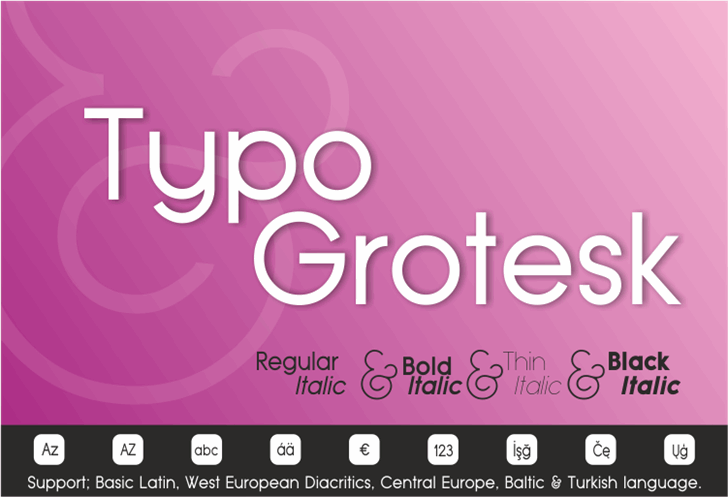
Typo Grotesk font family
A Typo Grotesk é uma tipografia sem serif que se destaca pela sua simplicidade e elegância moderna, perfeita para projetos digitais contemporâneos. Desenhada pelo designer Hamilton, ela oferece um equilíbrio entre leitura fácil e estética minimalista. Essa fonte suaviza a aparência de seus caracteres, tornando-a ideal não apenas para aplicações online, mas também para designs impressos digitais. Com uma tipografia como esta, você pode explorar inúmeras possibilidades criativas sem sacrificar a legibilidade fundamental que é essencial em um projeto moderno. Seja para aplicativos móveis ou websites, essa fonte oferece um toque de sofisticação sem comprometer o conforto visual. Para aqueles interessados no uso comercial desta fonte, Hamilton disponibiliza mais detalhes e opções através da sua página oficial.